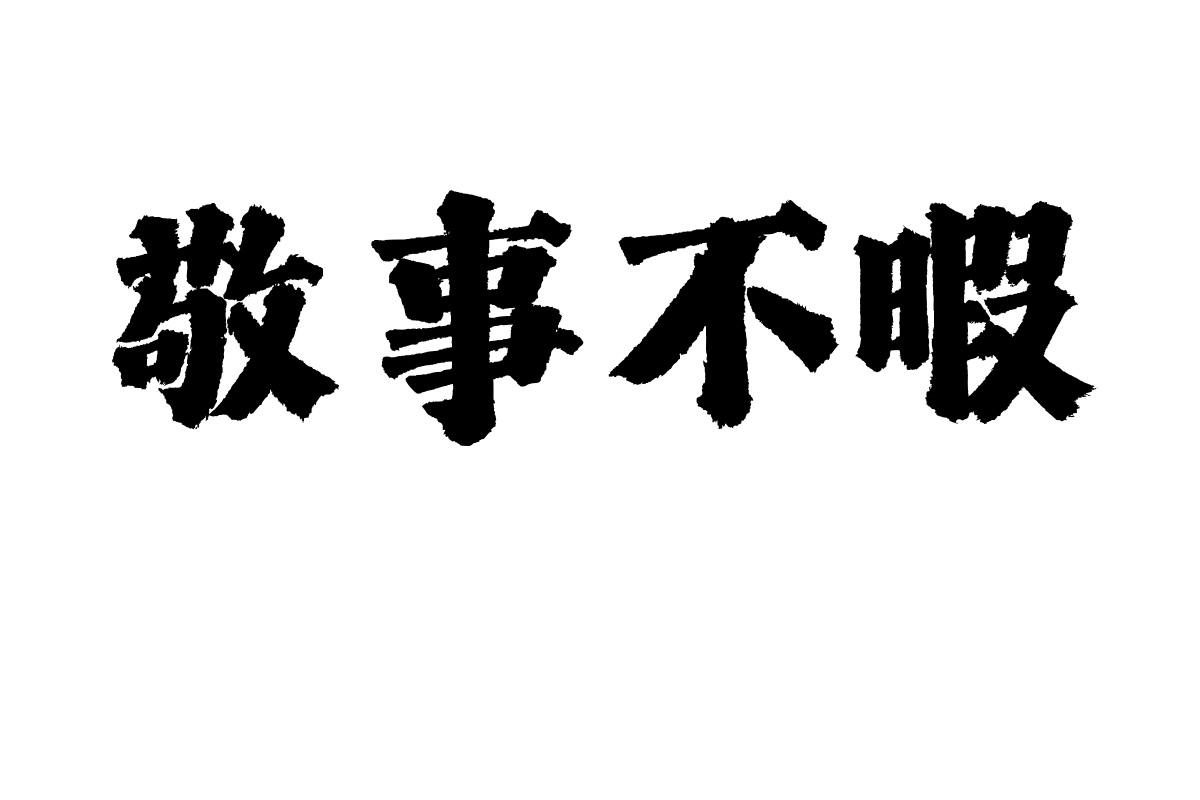
潮字社绝尘楷是一套由潮字社设计并发布的免费字体。这套字体具有现代、简洁和时尚的特点,适合用于商业、广告、网站等场合。
潮字社绝尘楷的笔画流畅,结构严谨,给人一种清晰、易读的感觉。它的字形大小适中,适合各种应用场景。同时,这套字体还具有一定的艺术感,能够吸引人们的注意力,增加视觉冲击力。
总的来说,潮字社绝尘楷是一款非常实用的免费字体,无论是在设计还是印刷方面,都能够提供良好的效果。